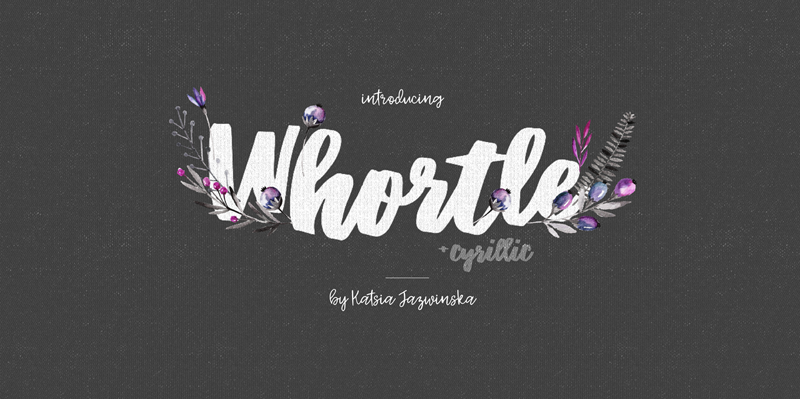
Whortle é uma fonte script que traz a essência do desenho artesanal para seu trabalho de design. Com suas formas ondulantes e sua disposição da linha de base dançante, Whortle tem um toque único que torna qualquer projeto mais personalizado. A fonte é especialmente adequada para textos em todas as letras maiúsculas e minúsculas, garantindo uma consistência rica e impecável. O grande conjunto de símbolos puntuais, números e suporte internacional também adicionam um toque sofisticado a Whortle. Whortle é perfeito tanto para o uso em texto simples quanto em textos mais complexos, proporcionando um charme único que torna qualquer design inovador. Suas linhas fluidas e desenhadas por Katsia Jazwinska garantirão uma experiência única de visualização em qualquer projeto gráfico ou tipográfico.
Designer: Katsia Jazwinska